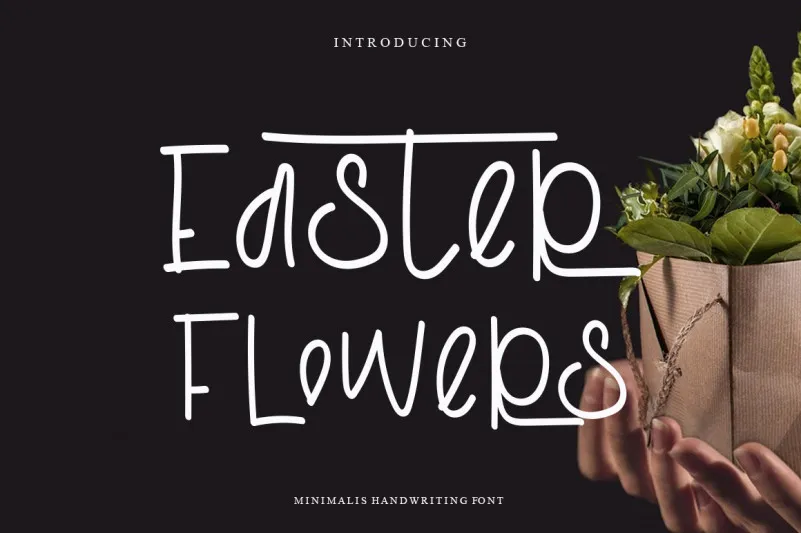
Easter Flowers Font – Fonte Grátis
Easter Flowers Font
Esta é uma fonte elegante, genuína e cursiva escrita à mão. Ela é perfeita para quem busca uma sensação aconchegante e romântica para seus projetos de design. Perfeito para adicionar um toque leve e encantador, tornando qualquer projeto mais atraente e envolvente. Ideal tanto para designers digitais quanto para aqueles que trabalham com papel, essa fonte criada pelo designer levincreative traz uma sensação docemente delicada que se assemelha à caligrafia escrita à mão. Suas linhas fluidas e suaves irão dar um toque único a qualquer projeto, seja ele um brochura de negócios ou uma carta de casamento, transformando-a em algo autêntico e pessoal. Seja para criar um design gráfico sofisticado ou decorar seu próprio diário com a mão, essa fonte escrita à mão leva a sensação de escrever algo que é verdadeiramente de coração. Uma escolha ideal tanto para aqueles buscando uma fonte única como para designers que desejam dar um toque especial a seus projetos pessoais ou profissionais.